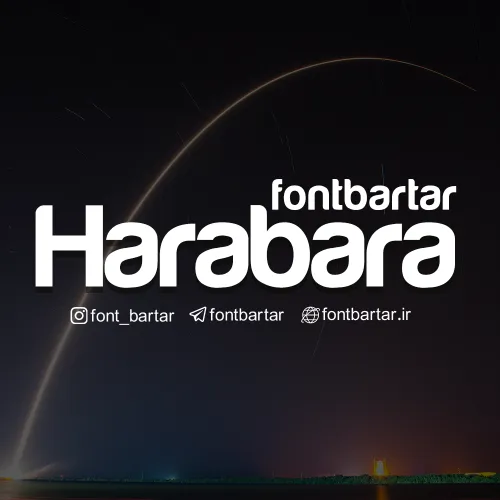
فونت اینگلیسی Harabara
فونت Harabara ، فونت زیبا و فانتزی با ساختار نرم و یکپارچه ، کاملا حرفه ای مناسب طراحی و همچنین استفاده در عنوان ها فونت اینگلیسی Harabara زیبا و خاص لاتین را از دست ندهید.
فونت اینگلیسی Harabara مورد استفاده برای:
• طراحان وب سایت و گرافیست های خلاق می توانند از این مجموعه زیبا فونت در طراحی پروژه های تبلیغاتی و تجاری خود کمک بگیرند.